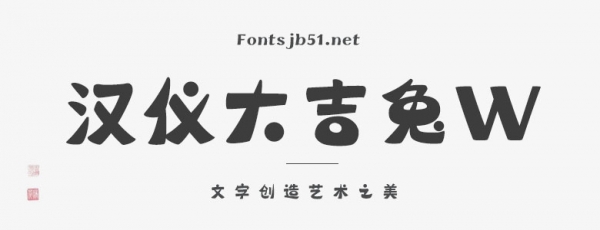
漢儀大吉兔是漢儀字庫與大吉兔聯(lián)合出品的一款創(chuàng)意字體。漢儀大吉兔的設(shè)計(jì)靈感來源于大吉兔軟萌的形象,融合了圖形構(gòu)成和微妙的手寫感。這款字體輕松可愛,適用于logo、標(biāo)題和短文案排版等場(chǎng)景。大吉兔是中式祈福文化的卡通形象IP,帶有擇吉祈福,助人心想事成的意蘊(yùn),旨在為大家?guī)ソ】?,?cái)富,愛情等好運(yùn)。